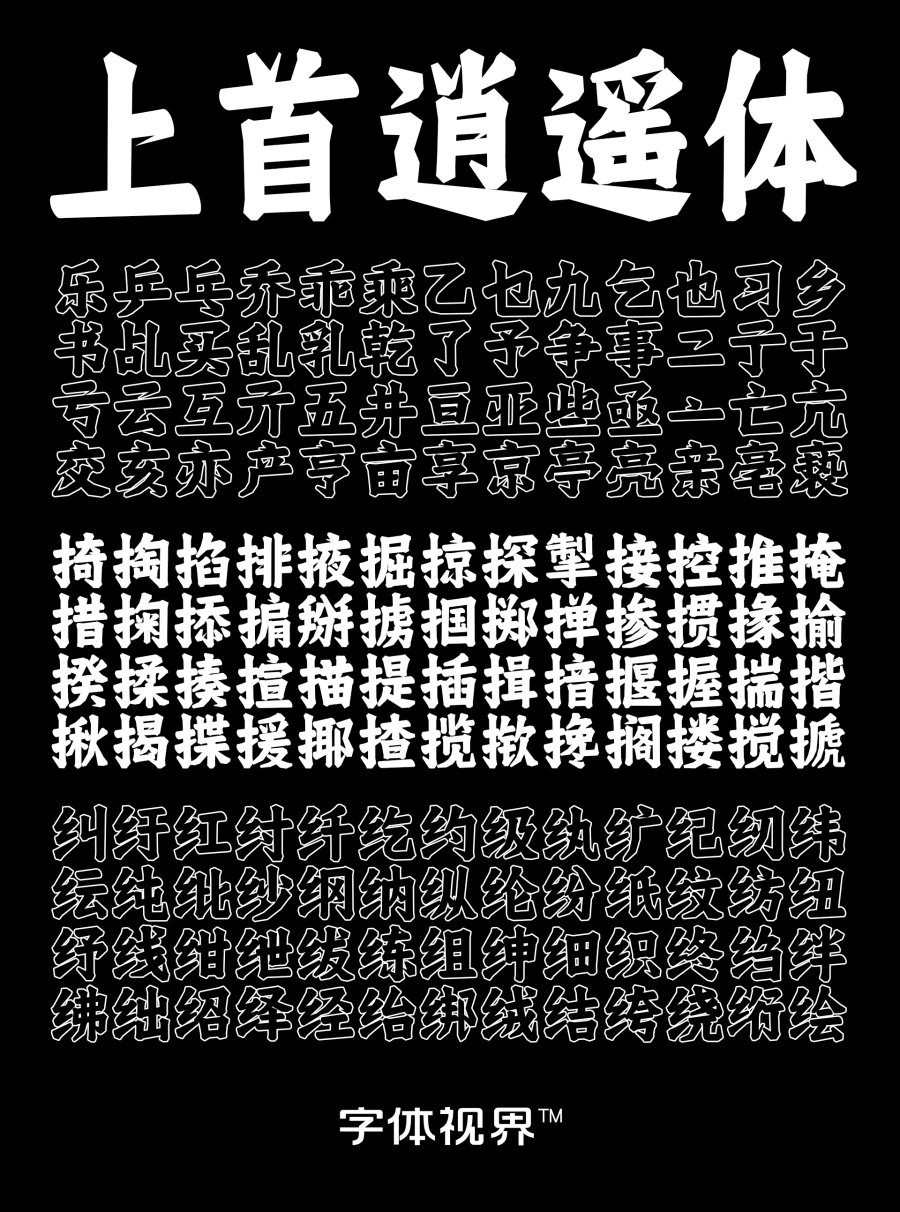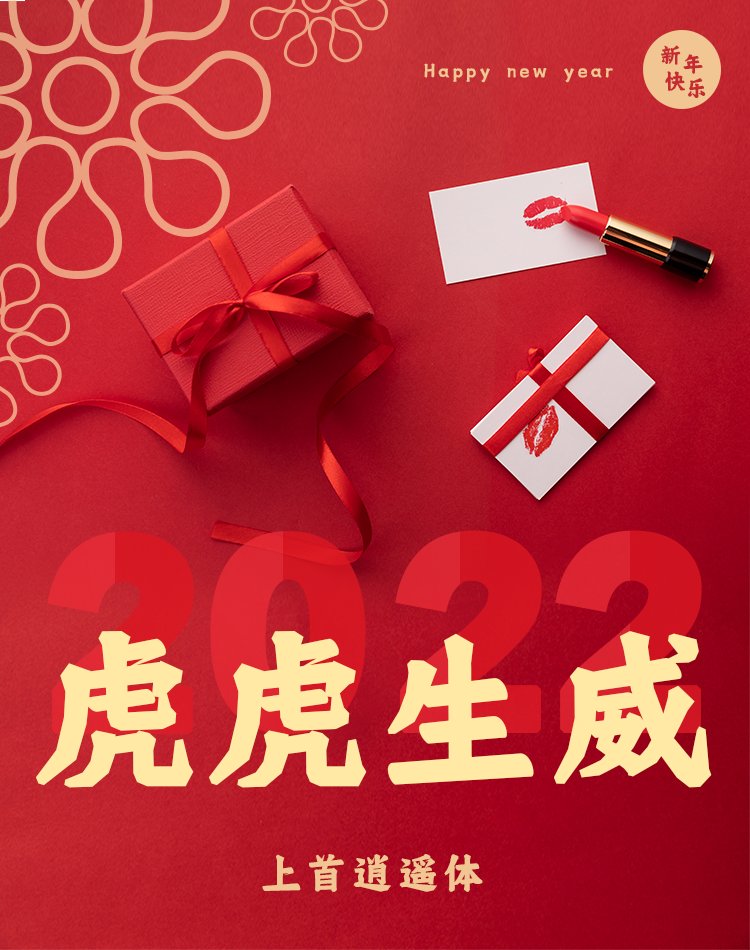
2022年伊始,上首造字团队又给我们带来什么样的惊喜呢?接下来,大家就跟随着字体视界的脚步,来看看上首造字团队近期上线这款新品艺术黑体「上首逍遥体」吧。
「上首逍遥体」字体笔画简约,随性而有个性,灵巧伶俐,橫笔两边导圆,竖笔收笔时带笔锋,撇捺收笔也带笔锋。
「上首逍遥体」符合国家标准简体字库GB2312所包含6763汉字,涵盖数字、英文和简体中文3种字体语言,适用于搭配标志、广告标语、商业广告等高端属性。完全可以满足设计师日常用字需求。